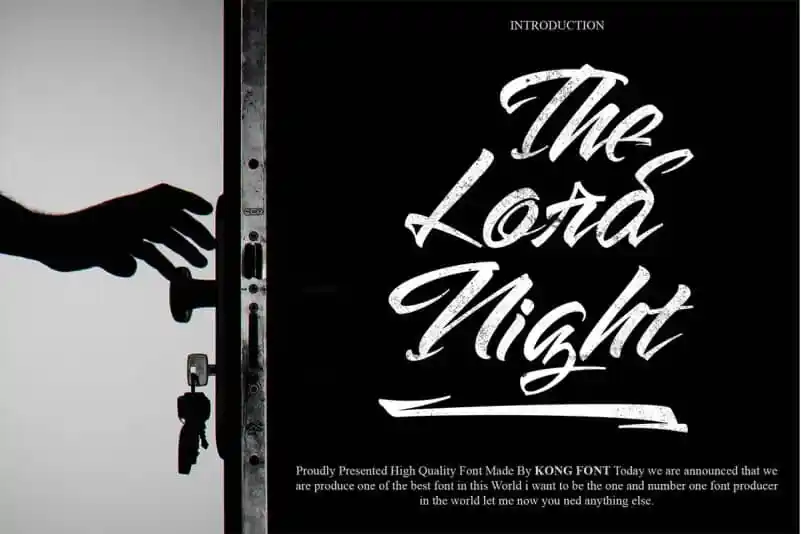
The Lord Night Brush Font – Download Grátis
Através do design inovador de 99designs, chegamos ao The Lord Night Brush Font, uma script font cuidadosamente criada para criar letras modernas e elegantes, tanto tópicas quanto impressionantes. Este recurso vem da mão do talentoso designer fontkong e inclui recursos abertamente opentype como alternativas estilísticas, conjuntos estilísticos e ligaturas. Perfeito para logotipos, camisetas, revistas, embalagens e qualquer tipo de design onde a elegância e o conforto da letra brilham. O The Lord Night Brush Font é uma opção perfeita se você busca uma fonte que combine modernidade com sofisticação em sua próxima criação visual.